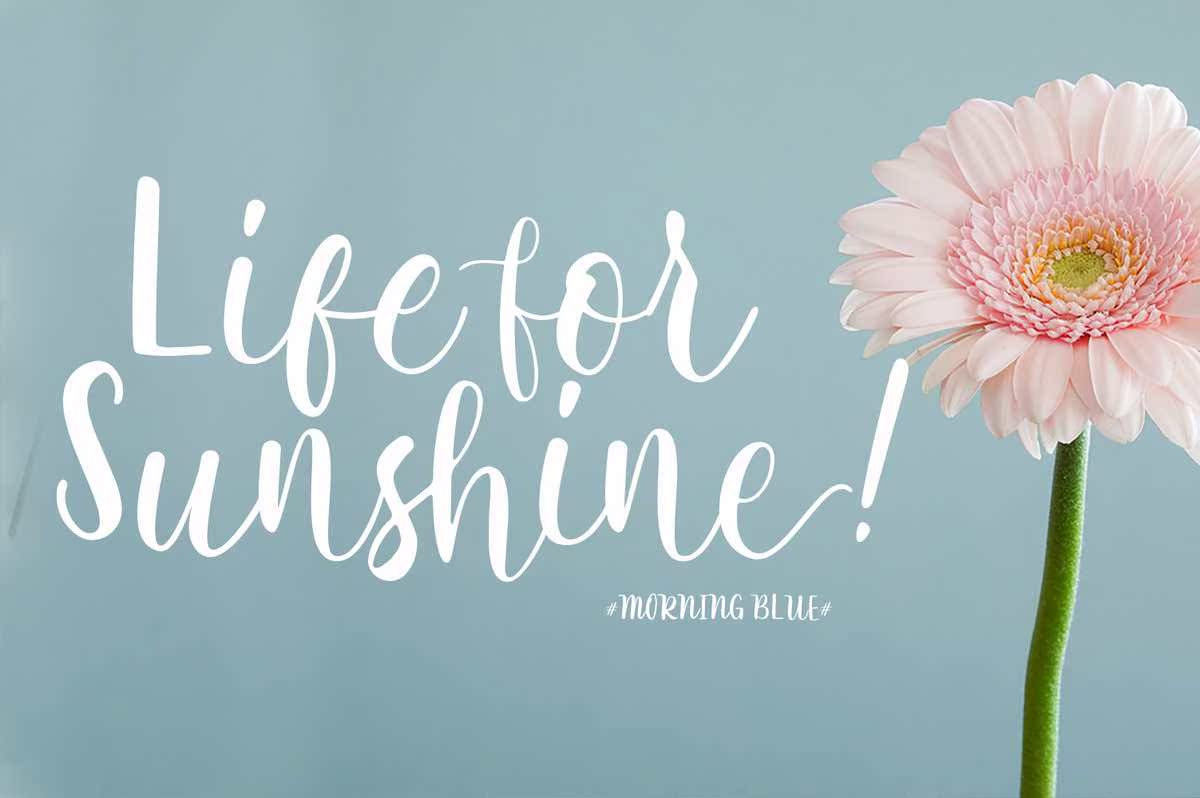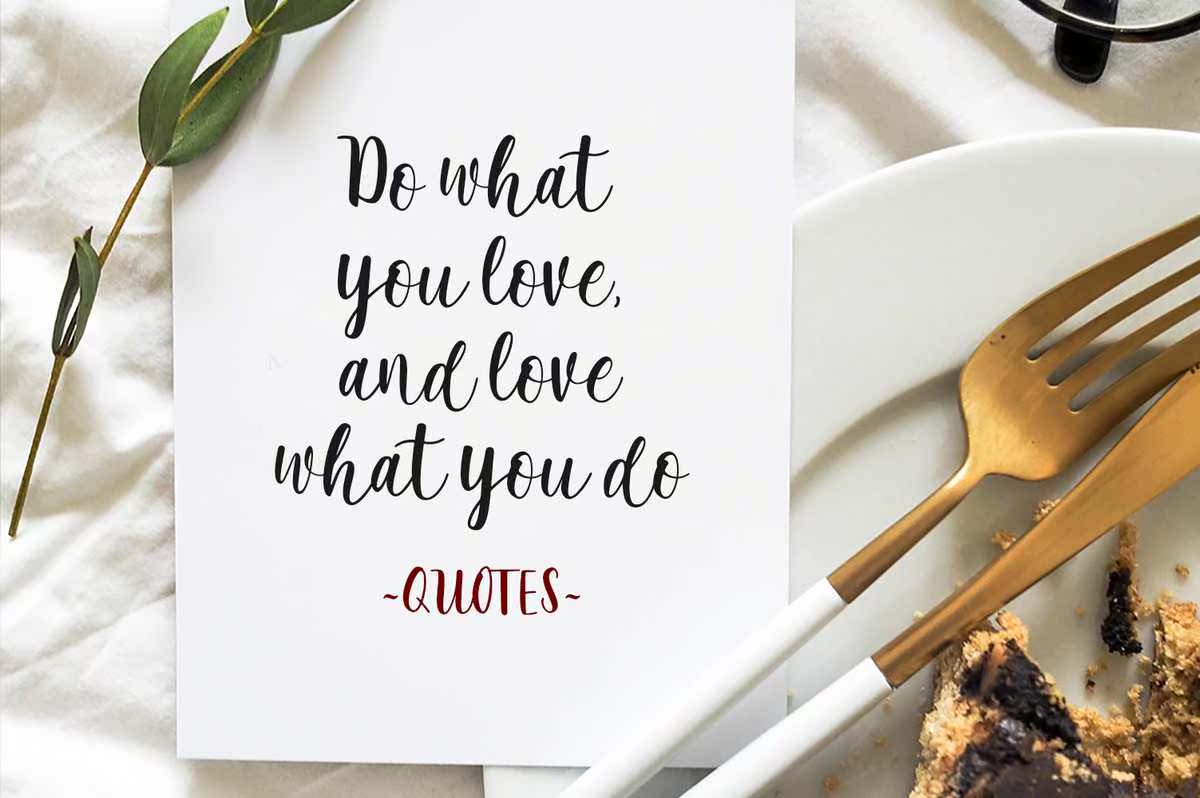
具有手写体风格的现代书法字体使此字体看起来简洁、优雅、自然,适合所有需要手写的项目。此字体适用于任何不同的项目,如徽标和品牌、邀请函、文具、婚礼设计、社交媒体、广告、产品包装、产品设计、标签、照片、水印、,特别的或任何东西。带有手写体的现代书法字体使这款字体看起来优雅、自然,并且非常适合于需要手写的项目。这款字体完美地体现了不同的项目,如徽标和品牌、邀请、文具、婚礼设计、社交媒体、广告、产品包装、产品设计、标签、,摄影、水印、特价商品或任何东西。